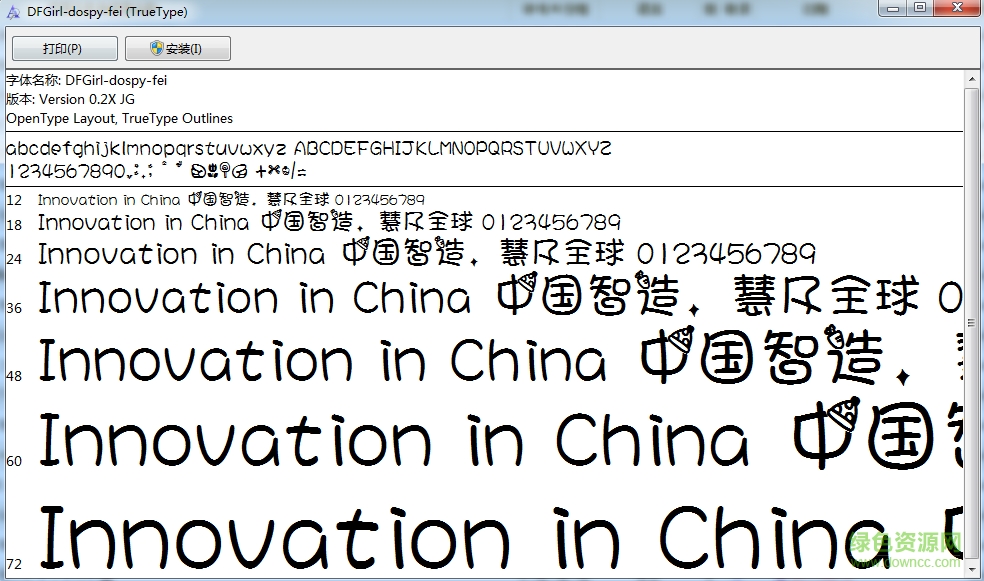
要當(dāng)學(xué)霸字體
學(xué)霸字體是一款菲比尋常的勵(lì)志級(jí)書法字體,學(xué)渣們趨之若鶩,字體簡潔娟秀,有學(xué)術(shù)研究之風(fēng),喜歡的朋友快來綠色資源網(wǎng)下載,成為學(xué)霸吧!
衡水學(xué)霸字體介紹
學(xué)霸字體得名于衡水中學(xué),高考文理科狀元層出不窮,有著濃郁的學(xué)術(shù)氛圍和考神光環(huán),本字體霸氣中帶著學(xué)究氣、輕松中又有著莊嚴(yán)風(fēng),不可多得的一款藝術(shù)字體,快來嘗試吧!
學(xué)霸字體
要當(dāng)學(xué)霸字體是一款用于藝術(shù)設(shè)計(jì)方面的字體,安裝后在系統(tǒng)中顯示DFGirl-dospy-fei,支持中英文輸入,繁簡體亦可。